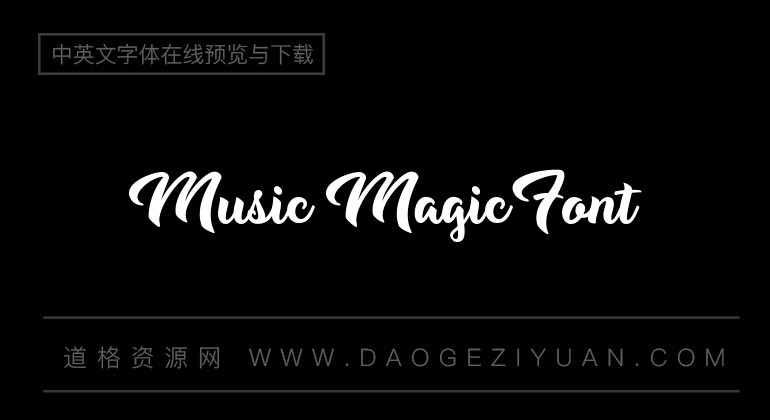
Music Magic Font 是一种音乐主题的字体,它的设计灵感来源于音乐符号和图案。它的字形流畅,具有现代感和艺术感,适合用于音乐类设计或相关专业领域的文本排版。 这种字体通常会用在音乐节目的海报、音乐教学材料、音乐图书和音乐电影的片头等方面,因为它的设计元素与音乐主题相吻合,可以很好地表现出音乐的节奏感和情感表达。同时,Music Magic Font 的字体风格也非常独特,能够吸引读者的注意力。 总的来说,Music Magic Font 是一种极具艺术感和创意性的字体,它适合用于音乐类专业的文本排版,能够营造出强烈的视觉效果和音乐感。内容介绍
Music Magic Font是一款非常不错的手写艺术字体,具有很好的视觉感,适合于文化类的宣传设计、商业类品牌的广告和产品包装设计以及个性化文字排版等较多场景。